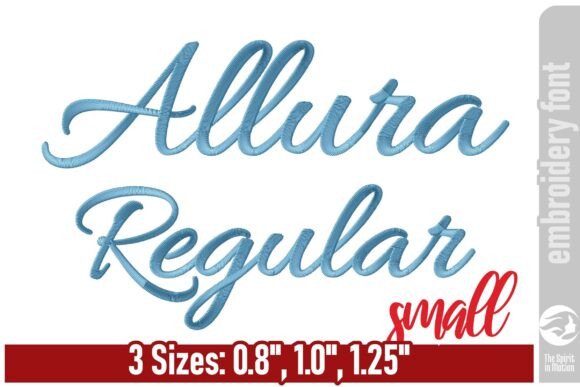
Allura Script Embroidery Font - Small
Mencari elemen reka bentuk yang sesuai boleh menjadi mencabar, tetapi Allura Script Embroidery Font - Small menawarkan koleksi luar biasa yang menaik taraf karya anda serta-merta.
Dicipta dengan ketepatan, Allura Script Embroidery Font - Small menyediakan vektor yang bersih, tipografi yang licin dan lesen komersial untuk ketenangan fikiran.
Sama ada anda mencipta produk POD (Print on Demand), jemputan perkahwinan atau grafik media sosial, Allura Script Embroidery Font - Small amat bersesuaian.